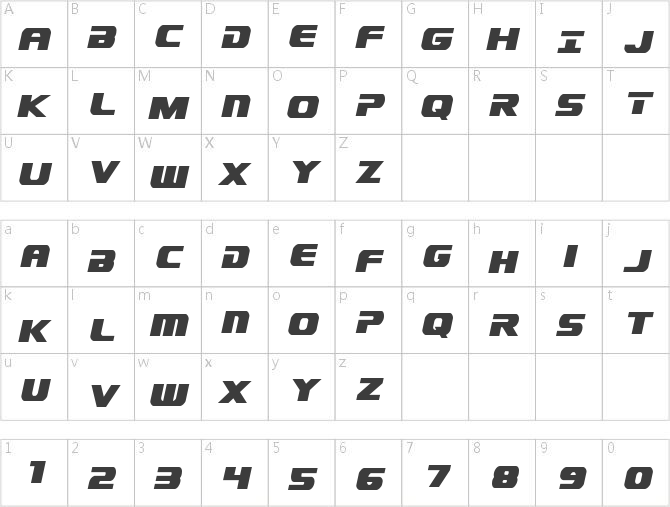
Dekaranger Condensed Italic
Dekaranger Condensed Italic介紹
Dekaranger Condensed Italic字體字庫是一款讓人賞心悅目、百看不厭的英文字體,適合各類廣告和產品包裝設計應用,字體大小0.03MB,格式為ttf字體,上傳用戶是gagilang,作者/版權方為未知